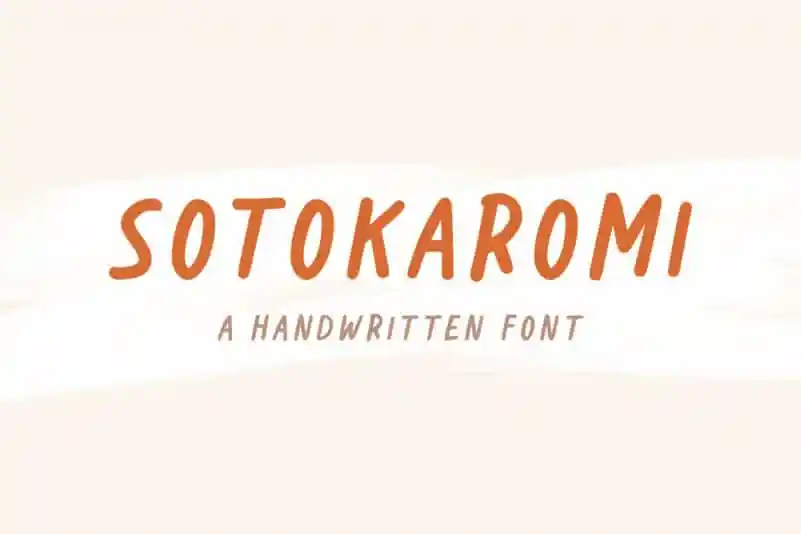
Sotokaromi Display Font – Download Grátis
A fonte Sotokaromi Display é uma elegante opção para quem busca uma personalidade única para seus projetos visuais. Este design handwritten oferece versões padrão e bold, adequado tanto para trabalho feminino quanto a criação de logomarcas, etiquetas de embalagem ou qualquer texto importante como títulos ou marcas de marca. Ideal tanto para um projeto mais sofisticado quanto casual, a Sotokaromi Display é uma opção versátil que pode ser usada em livros e capas de revistas, além de criações digitais. Seja você criando logos minimalistas ou estilos mais ousados, essa fonte oferece o equilíbrio perfeito entre elegância e personalidade. O Designer Jimtypestudio capturou a essência desses elementos para criar uma fonte que é tanto útil quanto atraente, adequada para uma ampla gama de aplicações. Não importa se você está criando arte digital ou um projeto gráfico tradicional: a Sotokaromi Display pode ajudá-lo a destacar seu trabalho e transformá-lo em algo memorável e imediatamente reconhecível.